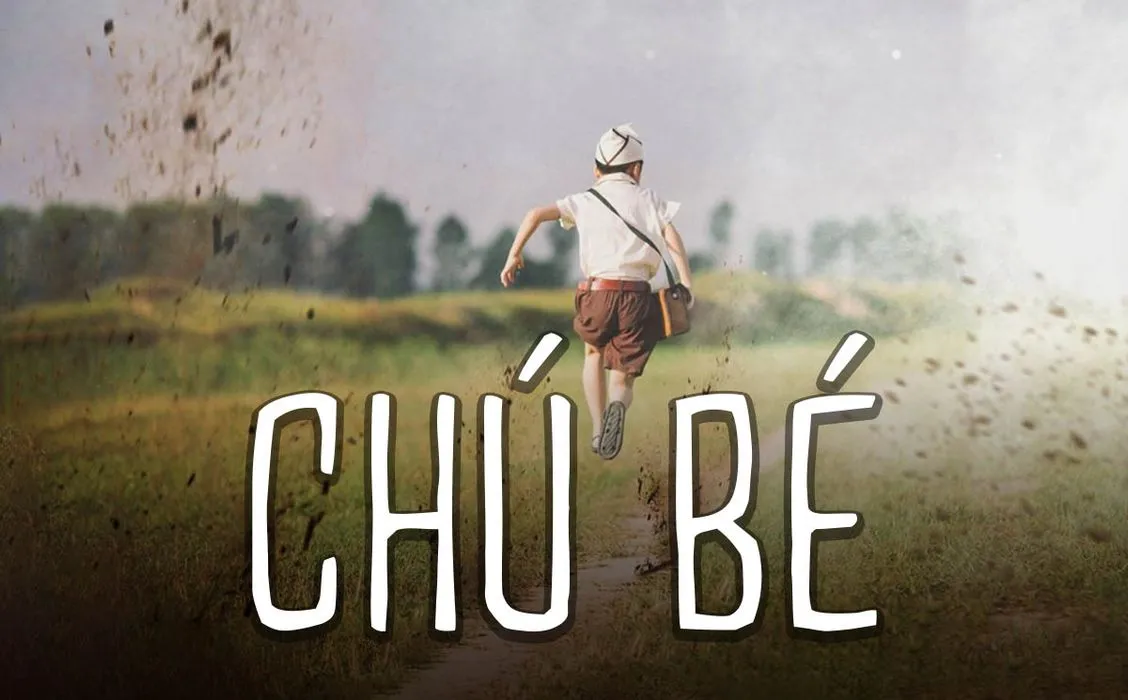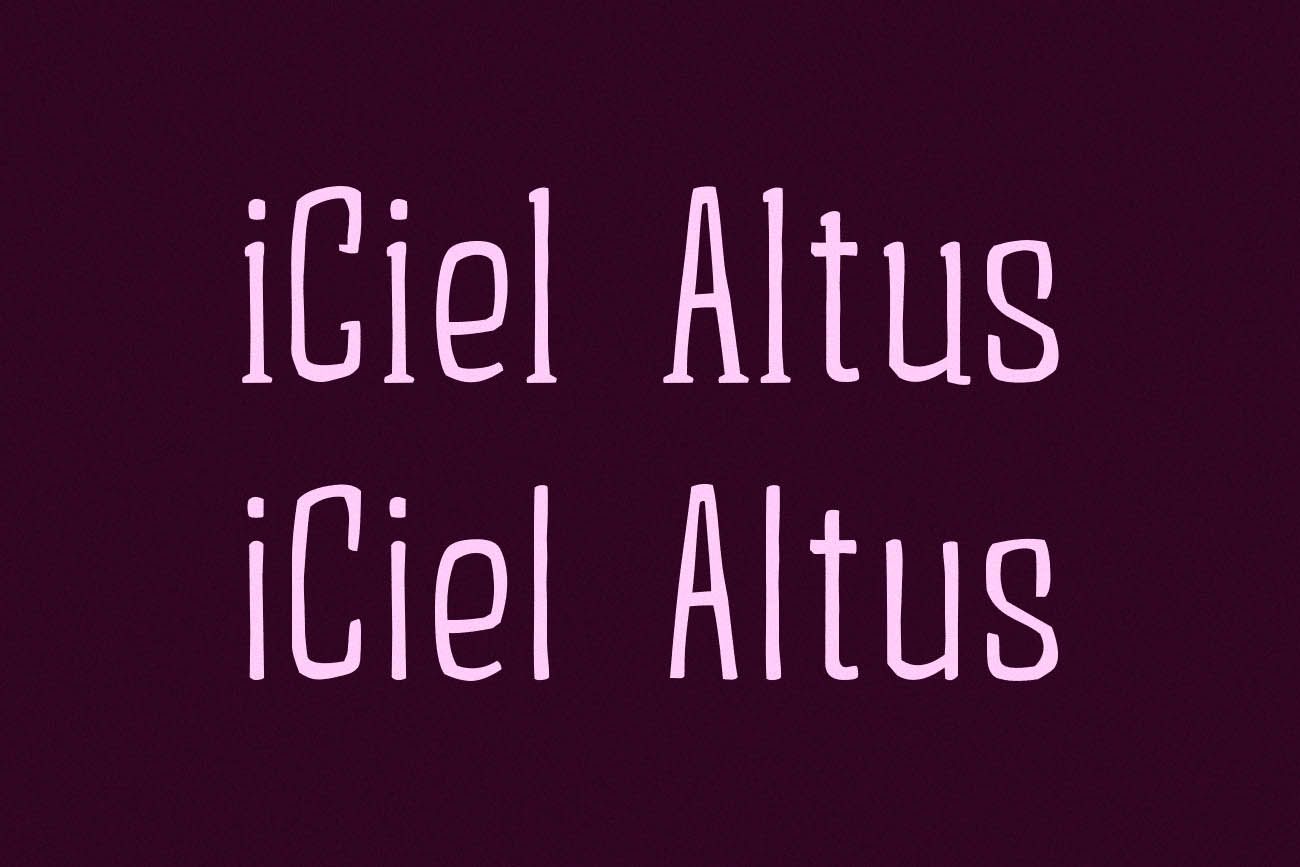
Trong thế giới typography, có những bộ font mang lại cảm giác gần gũi và thủ công đến mức khiến người xem tưởng như được chạm vào từng đường nét. Một trong số đó chính là font iCiel Altus – phiên bản Việt hóa từ bộ Altus Typeface của Jason Vandenberg. Đây là một font chữ handmade mang hơi thở vintage, rất thích hợp cho những thiết kế đề cao sự mộc mạc và cá tính.
Font gốc Altus được Jason Vandenberg sáng tạo với mong muốn tái hiện phong cách typography thủ công, pha chút hoài cổ. Khi được iCiel Team Việt hóa, font chữ iCiel Altus đã hỗ trợ đầy đủ dấu tiếng Việt, mở ra nhiều ứng dụng rộng rãi cho các designer trong nước.
Font iCiel Altus bao gồm hai biến thể chính:
Altus Regular: gọn gàng hơn, chữ cao và hẹp, dễ đọc, mang lại sự thanh thoát nhưng vẫn giữ nét thủ công.
Altus Rough: thô ráp, đường nét không đồng đều, tạo cảm giác như chữ in khắc gỗ hoặc viết tay, cực kỳ chân thực và cá tính.
Nhờ sự kết hợp này, bộ font vừa có thể dùng trong các thiết kế nhẹ nhàng, tinh tế, vừa phù hợp cho những dự án cần sự phá cách và mạnh mẽ.
Với tinh thần thủ công và hoài cổ, font chữ vintage Việt hóa này rất thích hợp cho:
Logo, bộ nhận diện thương hiệu của quán cà phê, tiệm bánh, cửa hàng thủ công mỹ nghệ.
Poster, bìa sách, tạp chí phong cách retro.
Bao bì sản phẩm, nhãn mác cần sự gần gũi và tự nhiên.
Thiết kế typography nghệ thuật, trích dẫn trang trí.
Nếu bạn đang tìm kiếm một font chữ handmade độc đáo, vừa gần gũi vừa có cá tính mạnh mẽ, thì font iCiel Altus chính là lựa chọn lý tưởng. Với phiên bản Việt hóa hoàn chỉnh, bộ font này chắc chắn sẽ giúp các nhà thiết kế tại Việt Nam tạo nên những tác phẩm mang đậm dấu ấn cá nhân và phong cách vintage đầy cuốn hút.